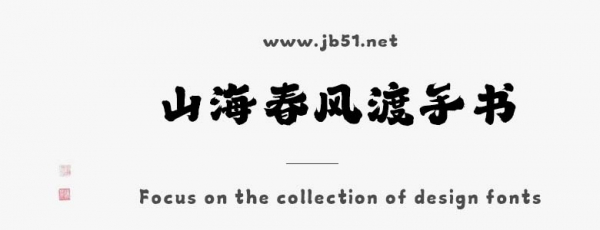
山海春風(fēng)渡手書(shū)W是由山海字庫(kù)出品的字體,這款字體筆觸略粗,具有很好的視覺(jué)感,適合應(yīng)用于藝術(shù)設(shè)計(jì)、平面宣傳設(shè)計(jì)、網(wǎng)頁(yè)設(shè)計(jì),書(shū)法字帖等領(lǐng)域,需要的朋友可以前來(lái)本站下載。